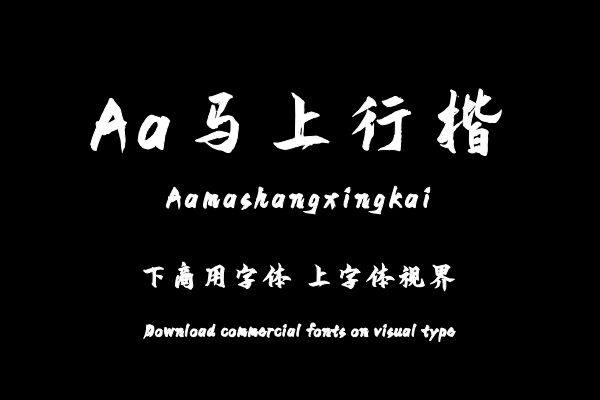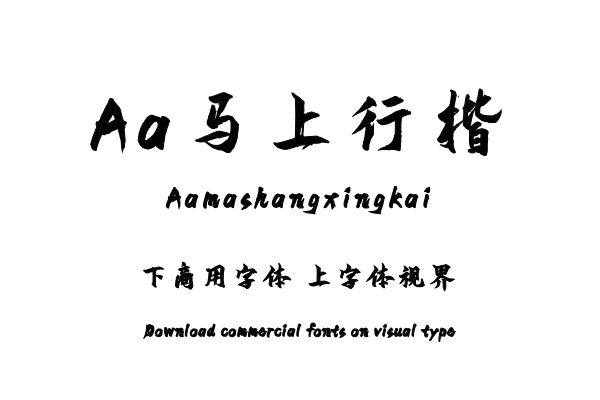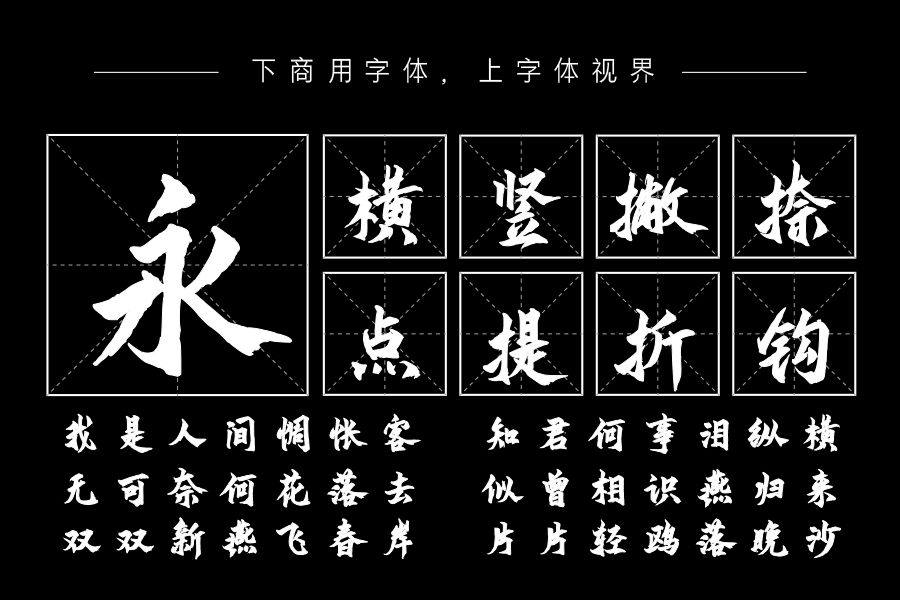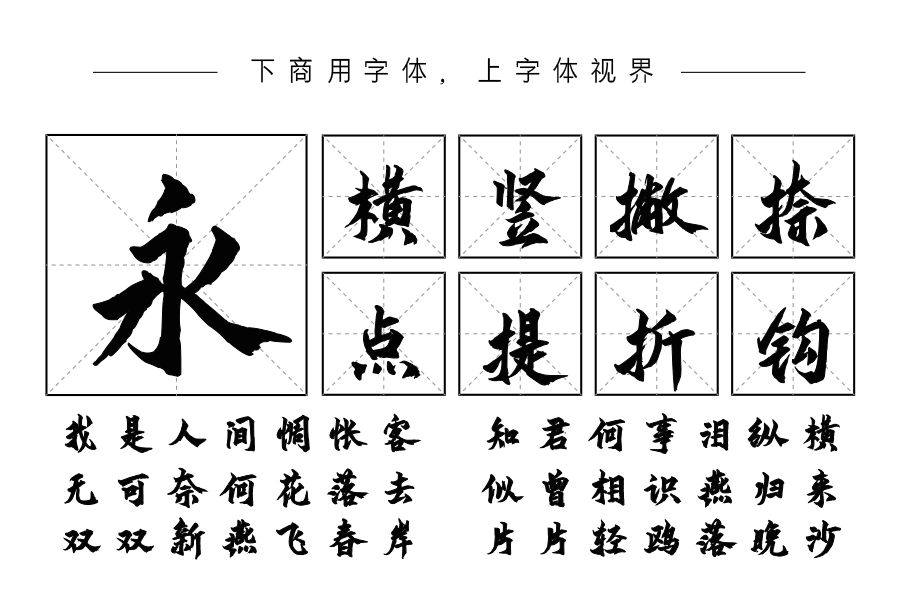
豪迈的书法字体是市场上比较受欢迎的字库形式,我们从风格出发融合作者自己的书写习惯制作一款特征鲜明的手书字体。以锐利的破锋构造的一款新派行楷,宛如回到战旗烈烈、战......购买须知:“下载服务费”与“字体VIP”所获得字体 仅用于个人非商用, 商用请联系付费授权。本字体为电脑用字,手机没有root权限不支持直接手机换字(手机如何root,请自行百度搜索教程)。购买前请先 了解清楚后再付款 ,字体为虚拟产品无法回收 一旦购买不支持退款。